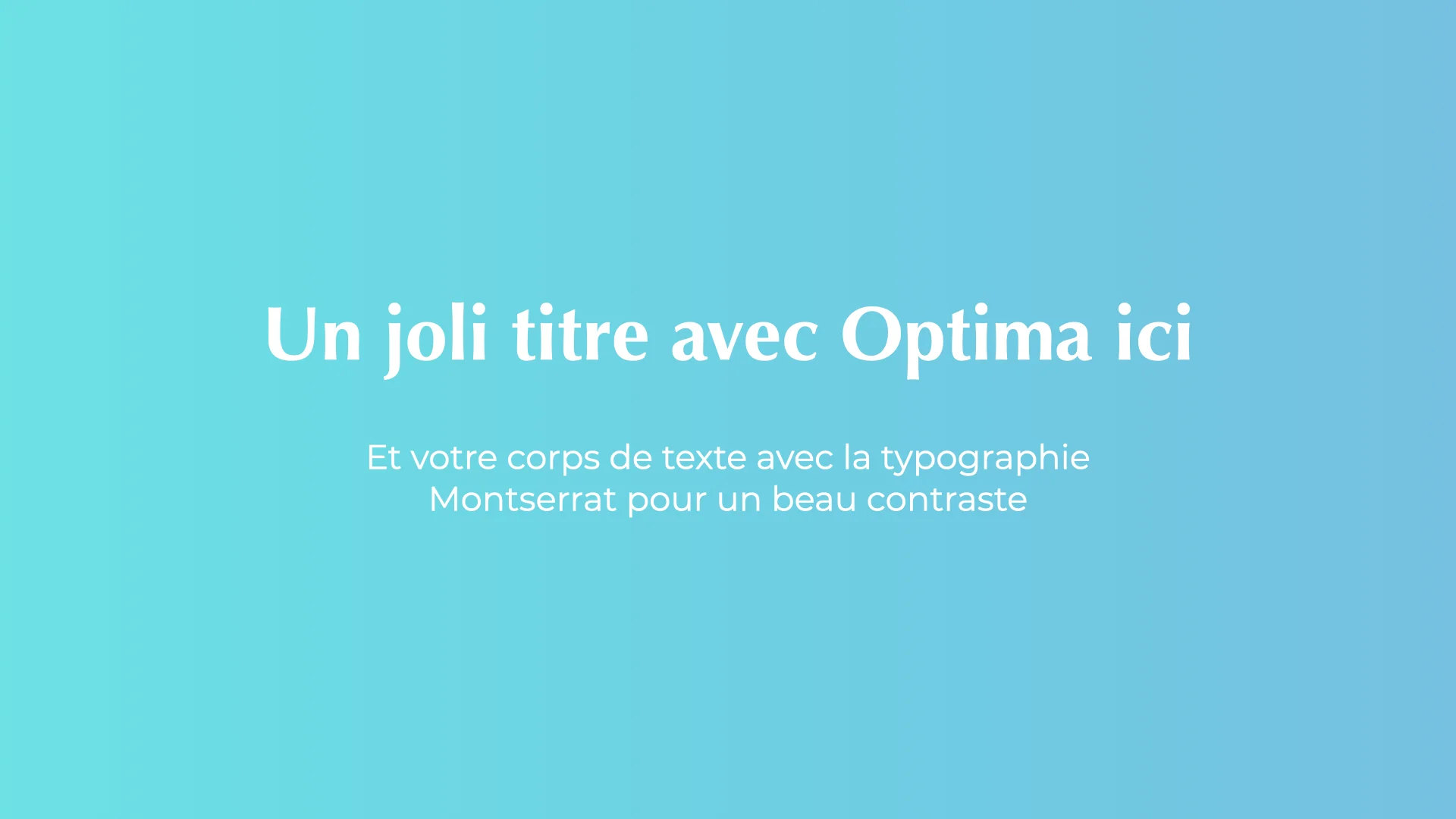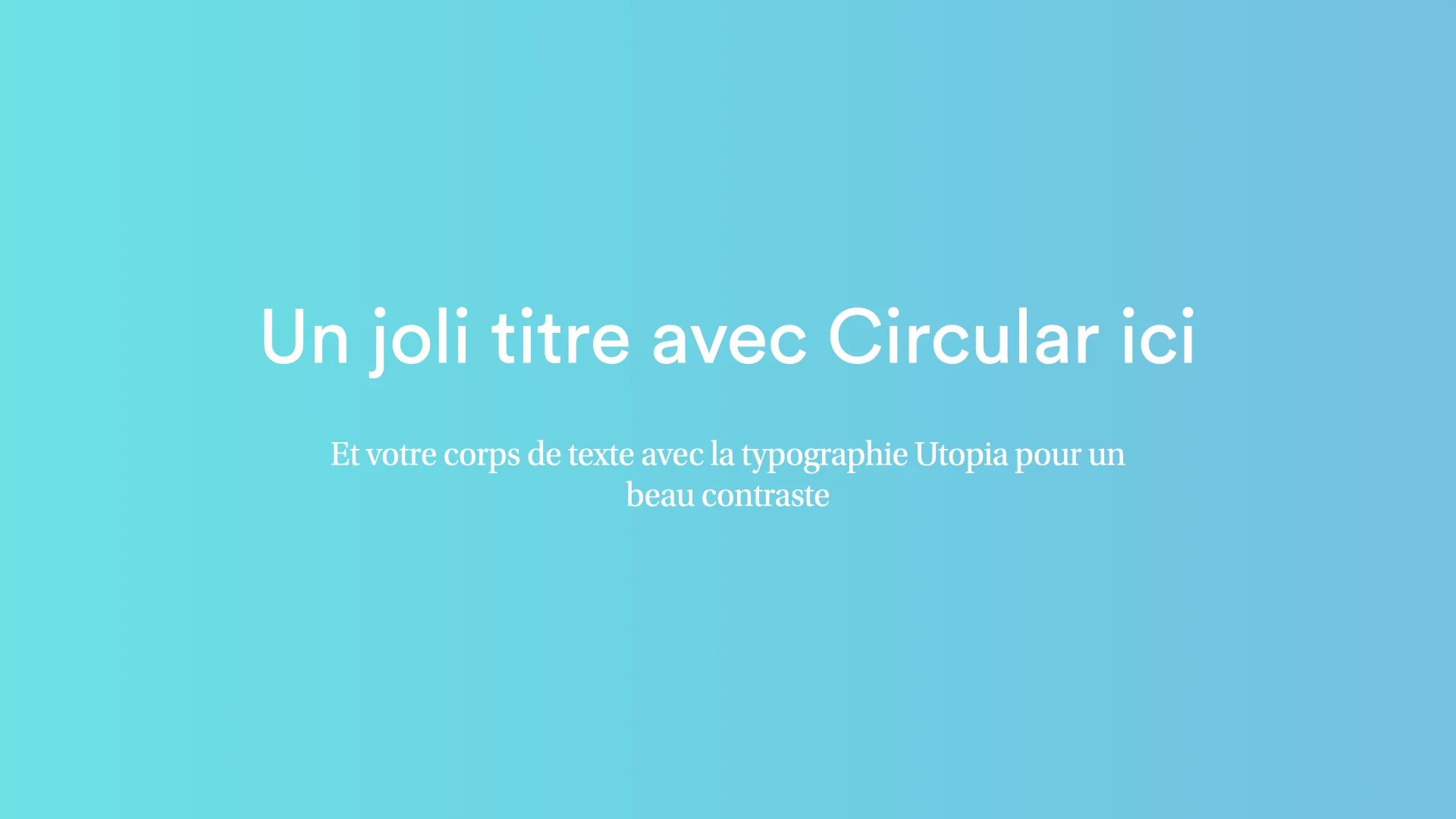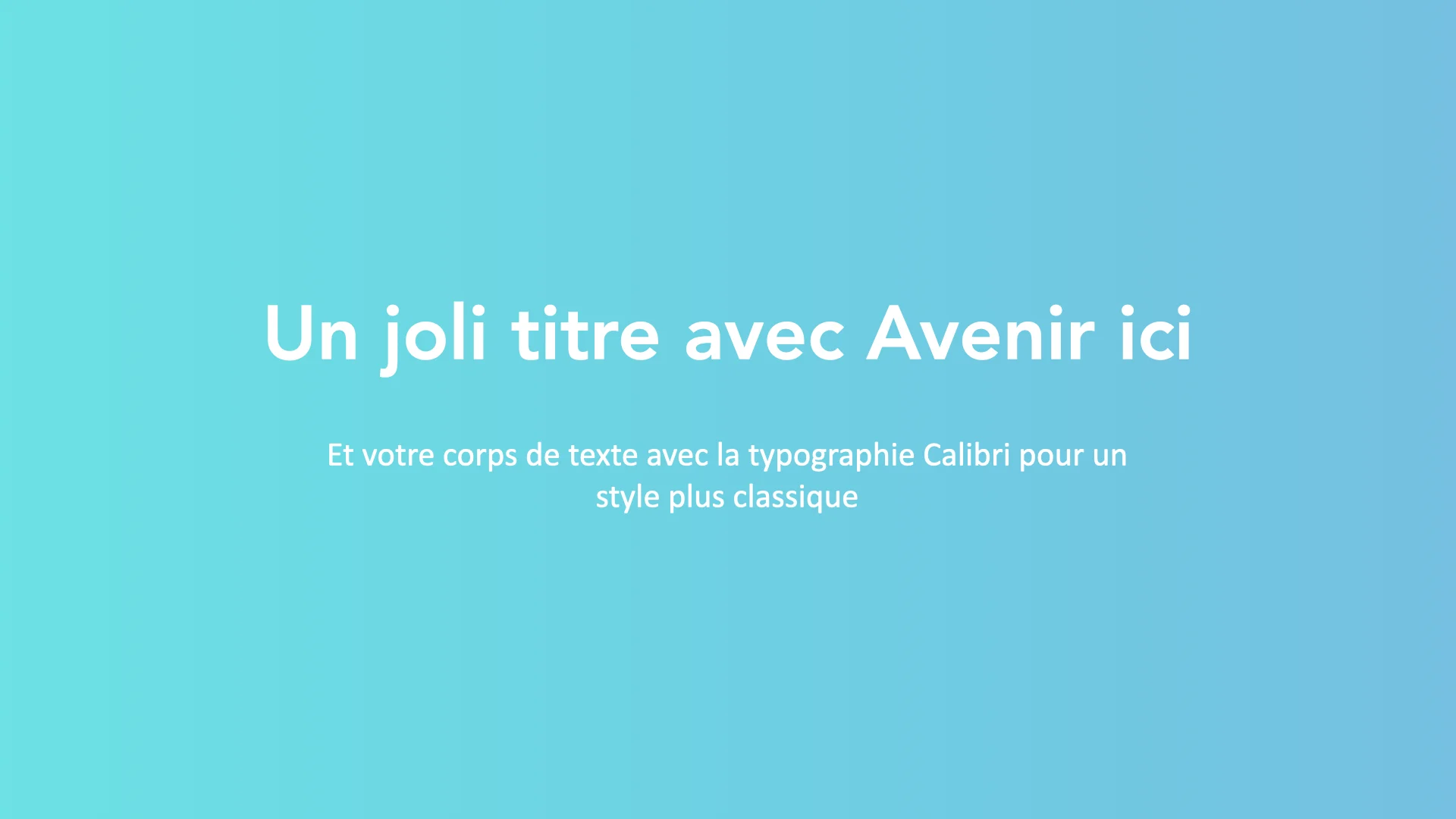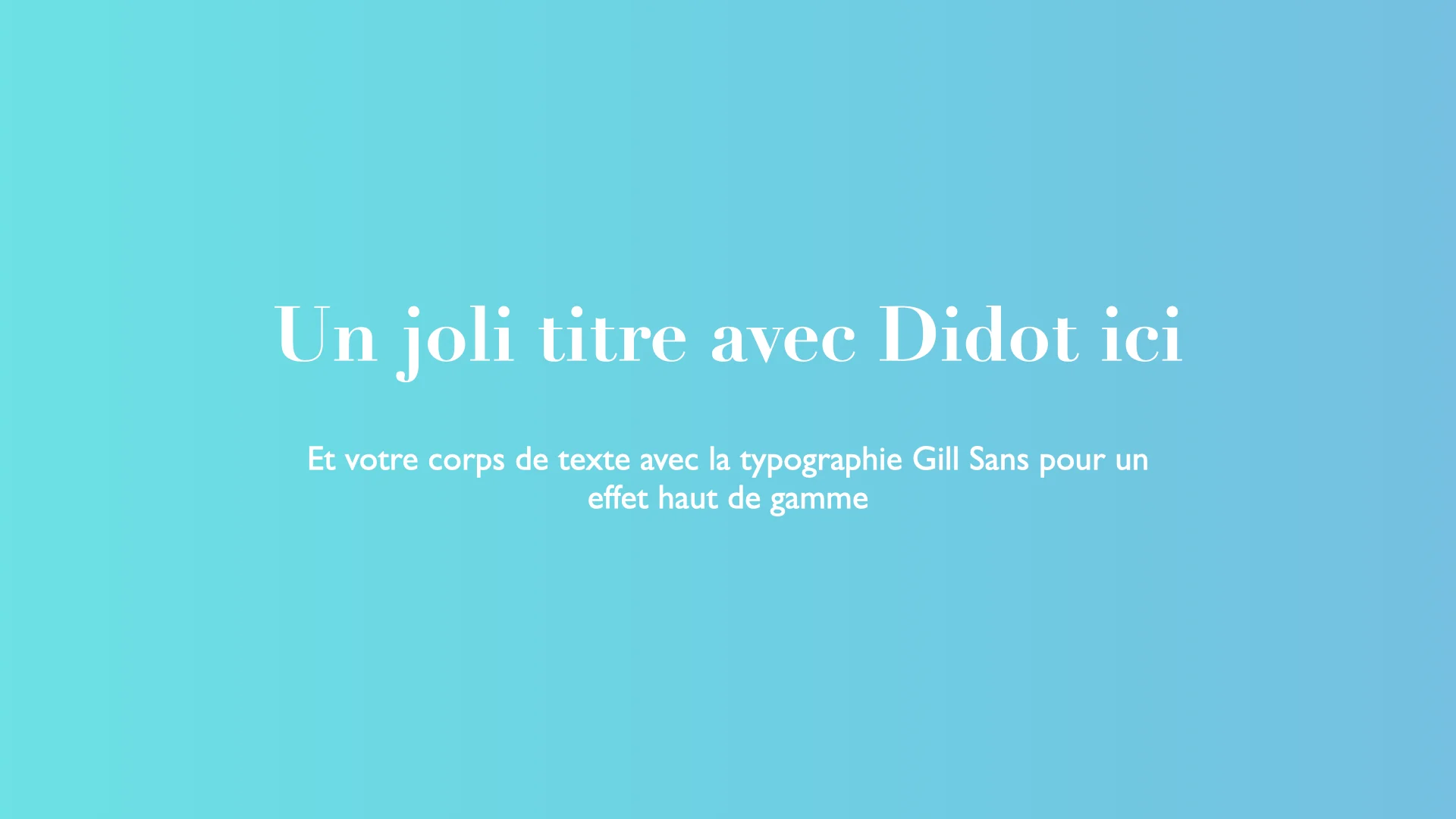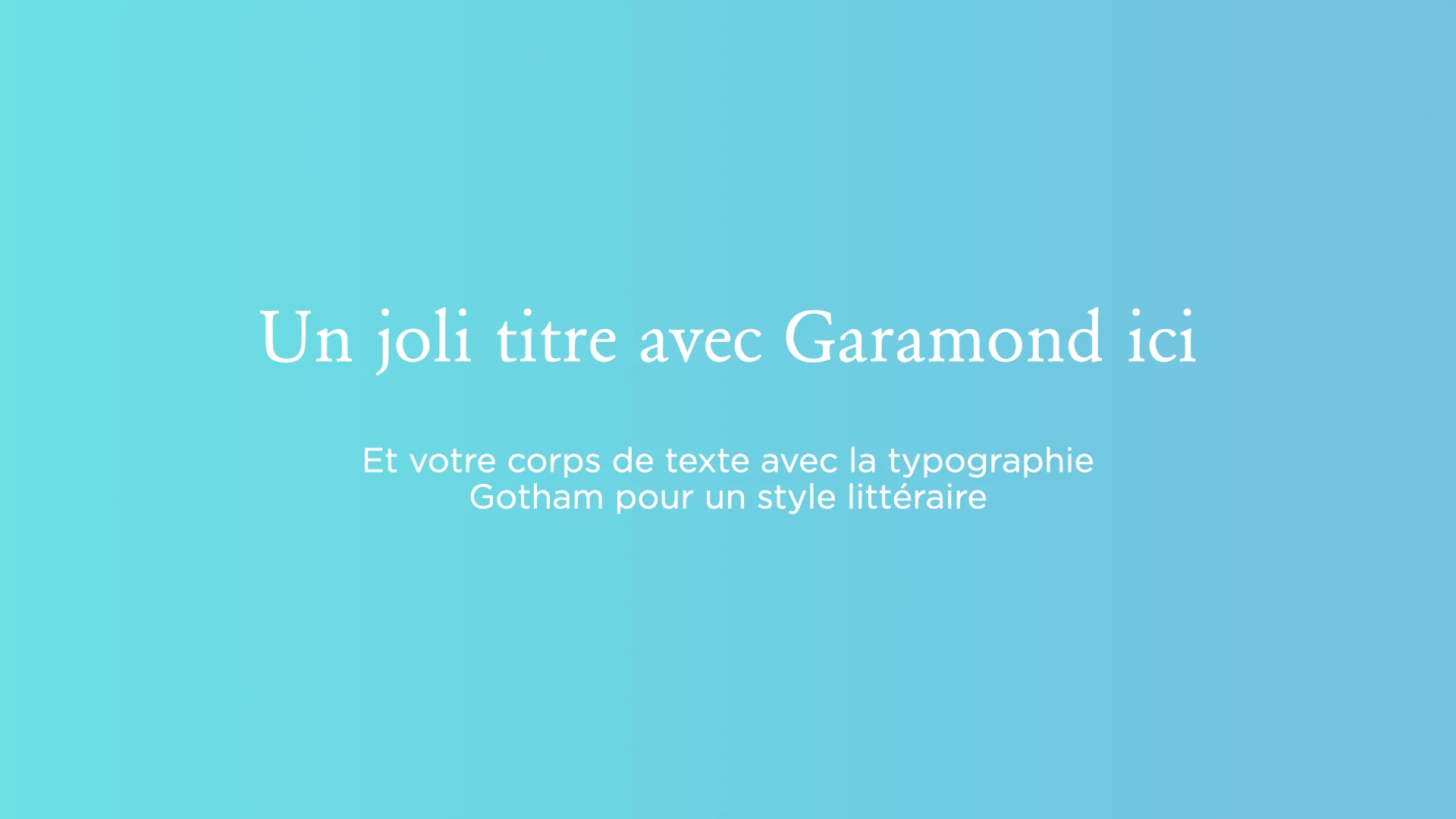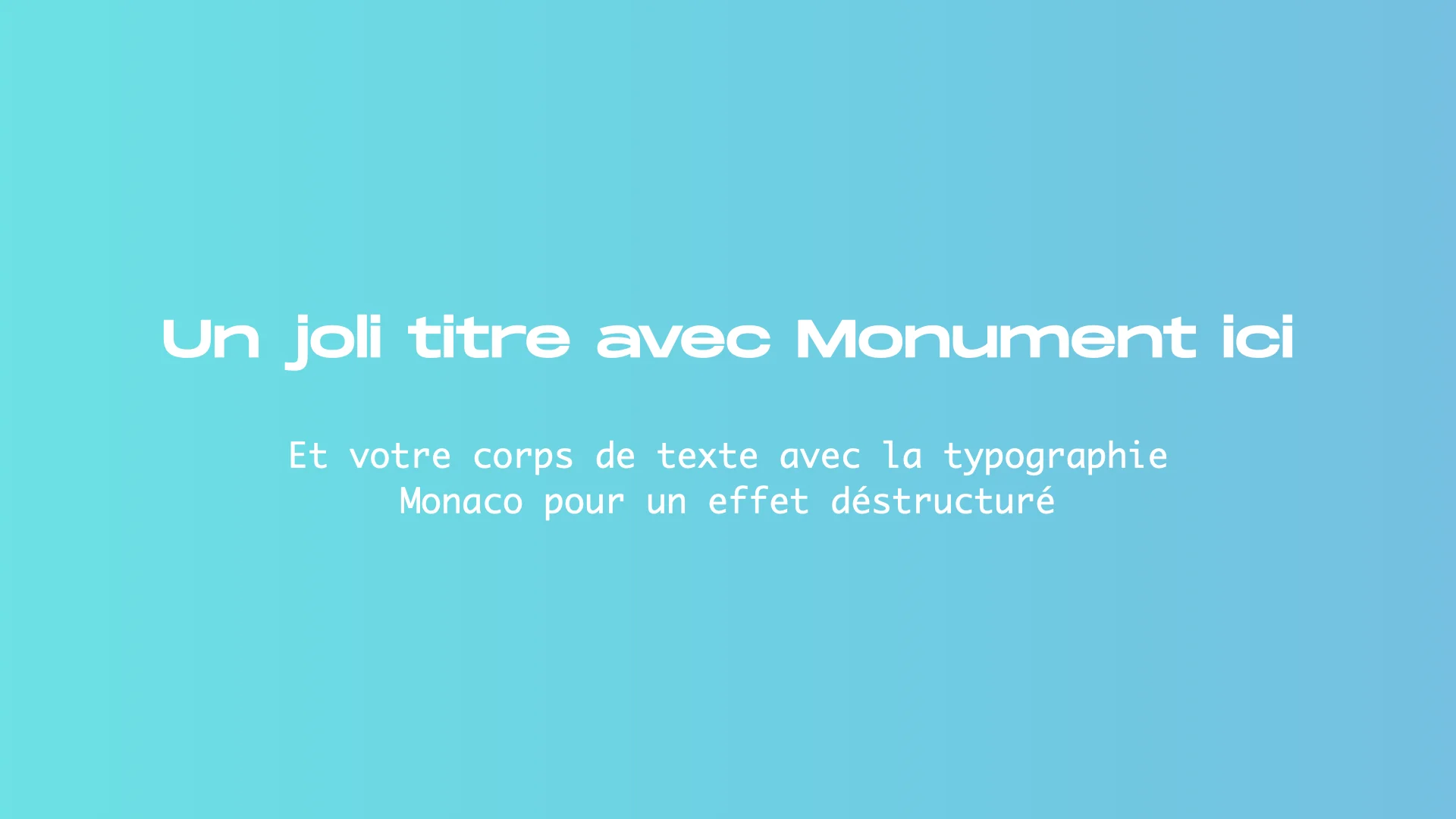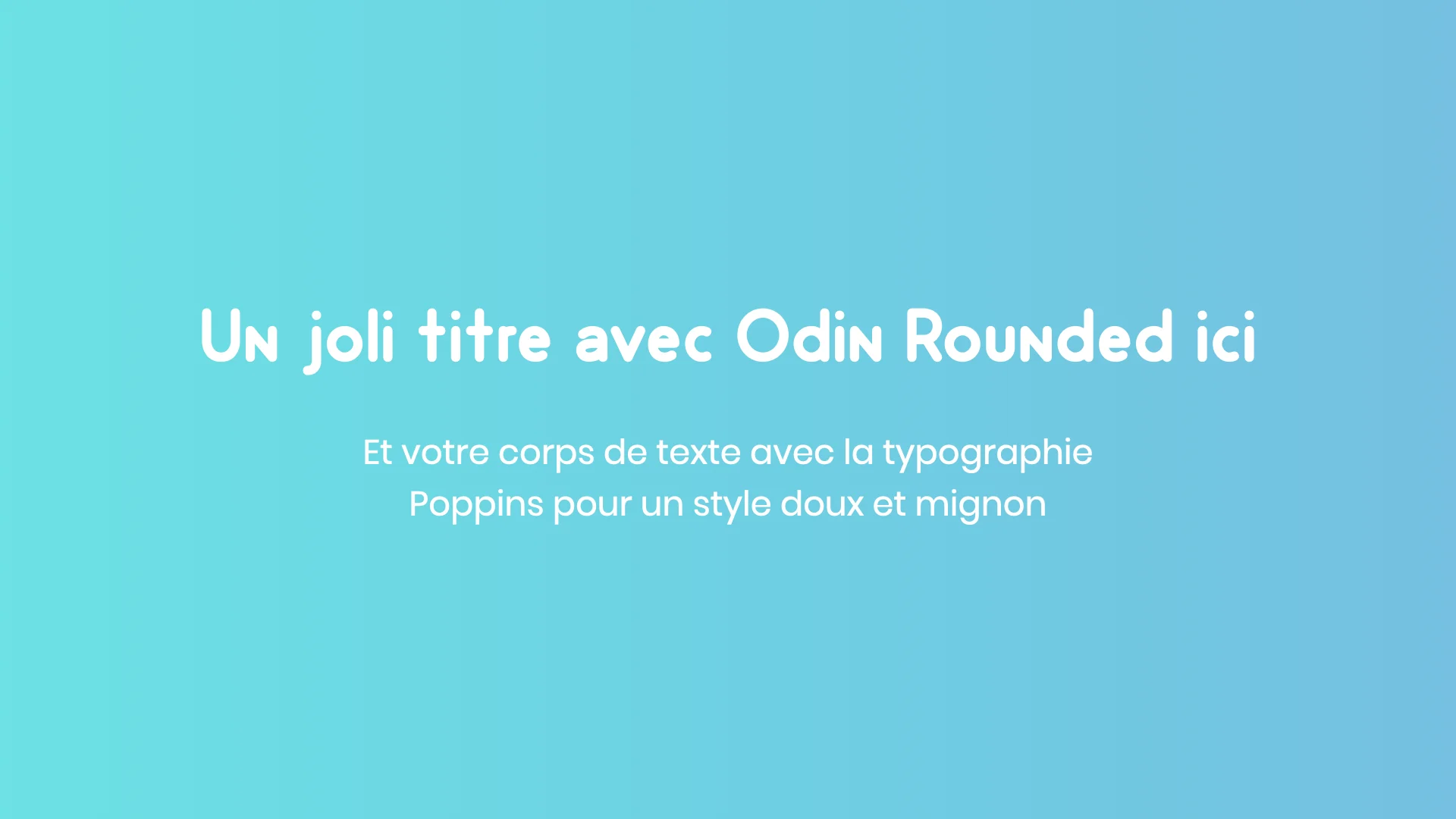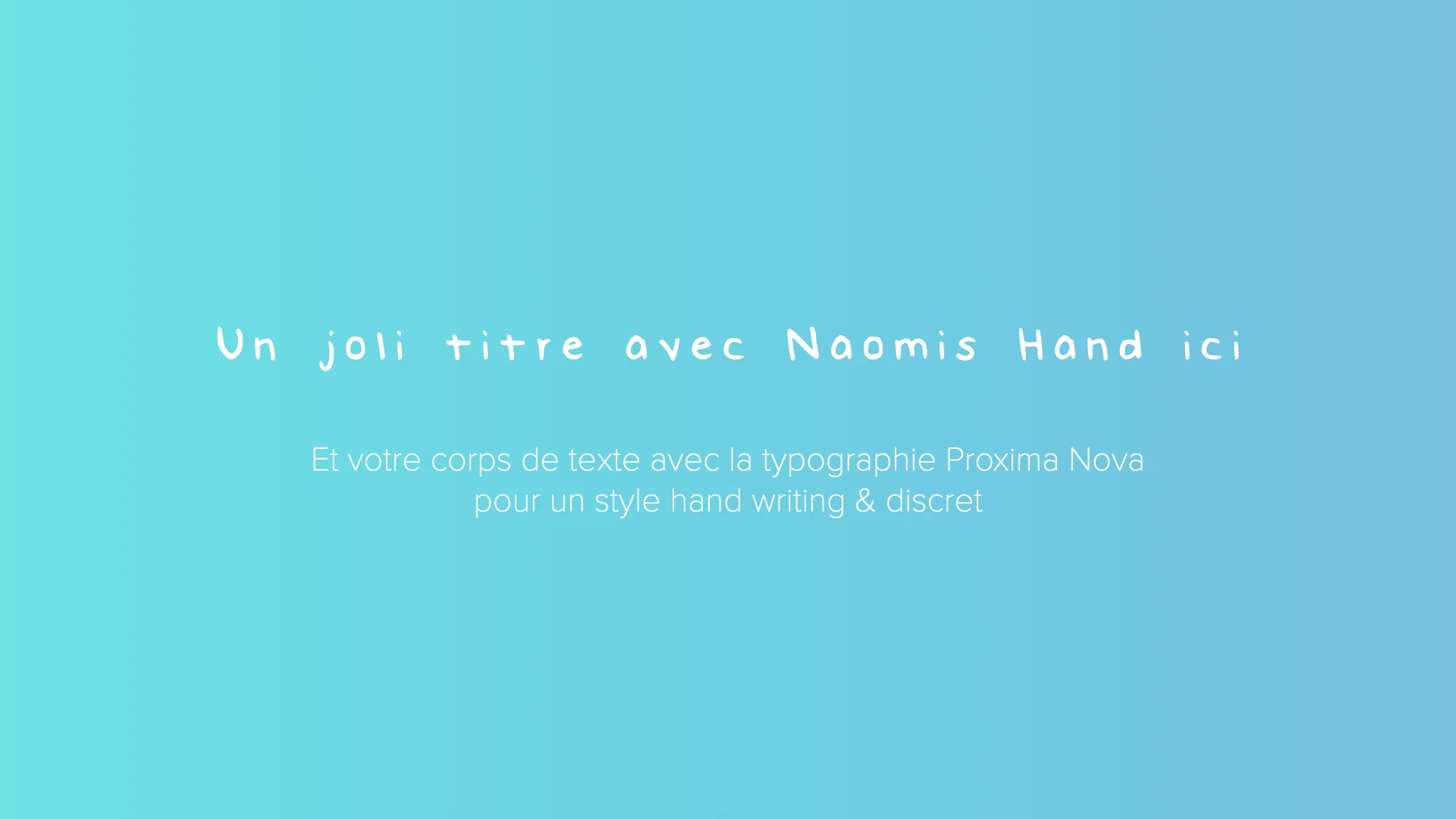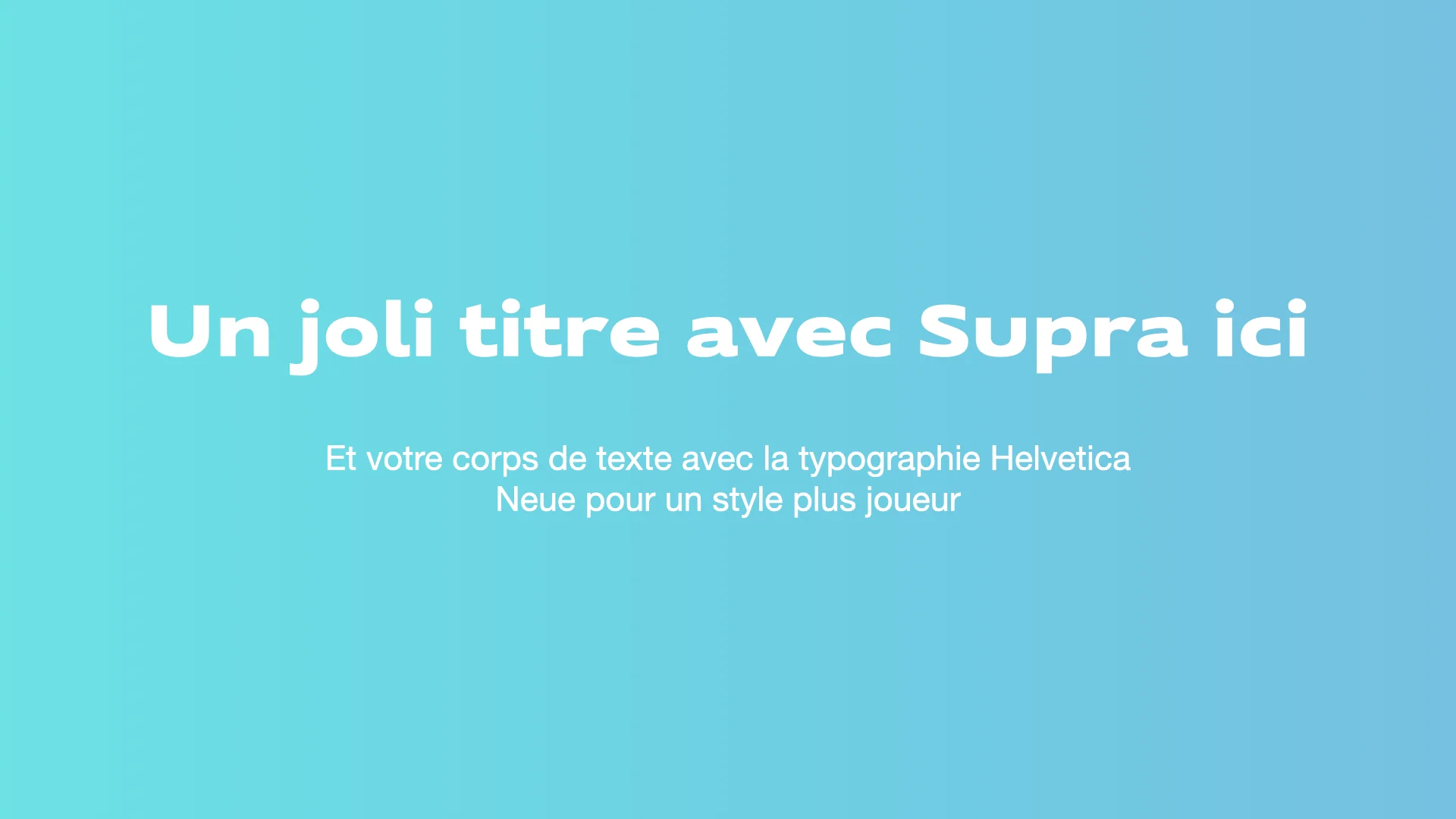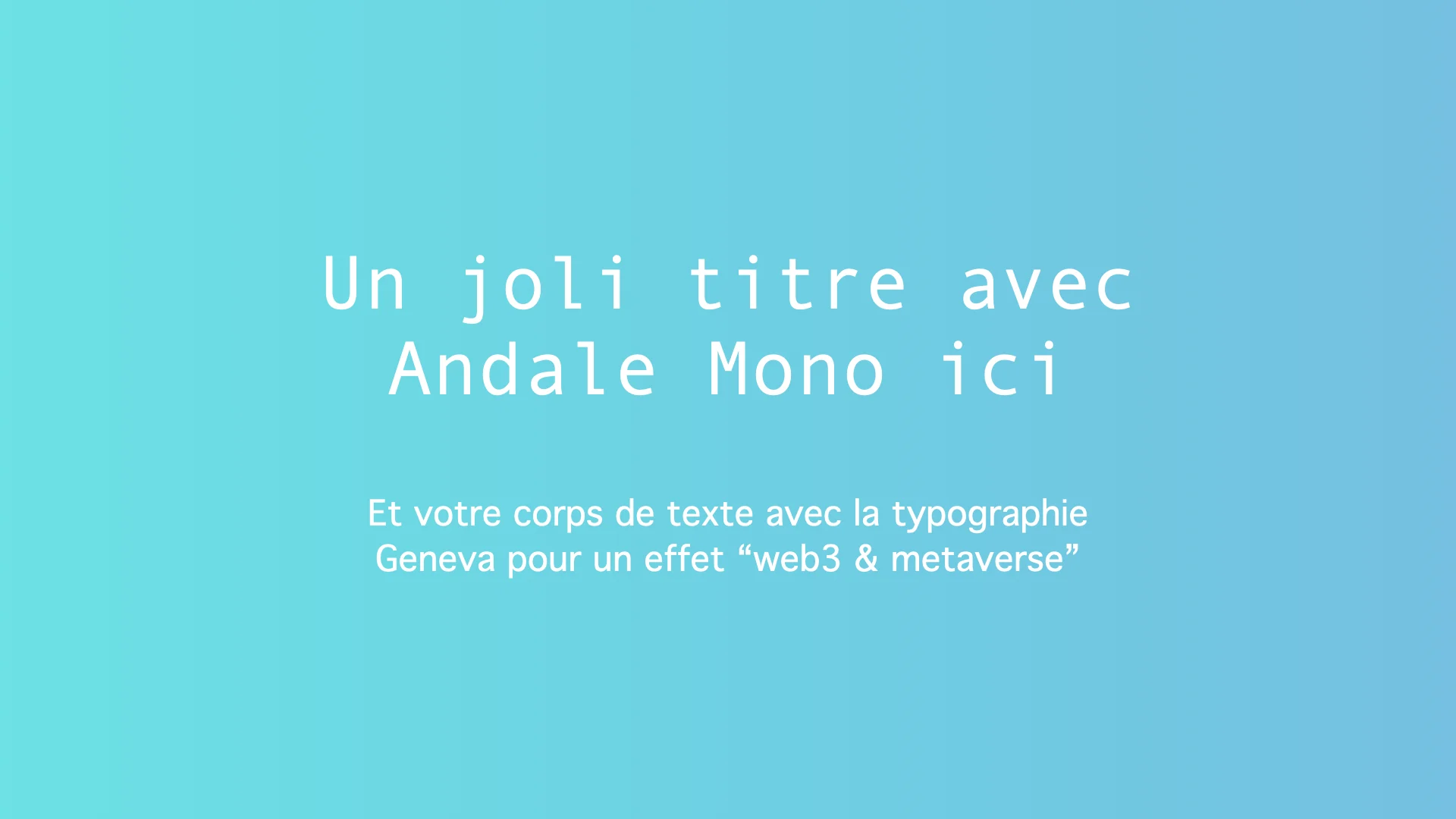
10 combinaisons de typographies pour vos projets 💑
Trouver des typographies complémentaires, ce n’est pas de tout repos. C’est pourquoi on vous propose aujourd’hui quelques idées faites maison histoire de vous aider dans vos recherches… et booster votre inspiration !
Quand on se lance dans un projet, que ce soit un nouveau business, une direction artistique pour une marque ou une présentation Keynote, il est essentiel de bien choisir ses typographies. En effet, vous le savez, elles symbolisent plus qu’une simple écriture. Elles permettent de véhiculer une idée, faire entrer un lecteur dans un univers, une atmosphère.
Cela parait plutôt logique, mais il est essentiel de rappeler qu’une bonne association de polices fait partie intégrante d’une charte graphique, que ce soit pour un simple visuel ou pour une plateforme de marque. Pourtant, c’est parfois difficile de trouver de bonnes combinaisons en fonction du message qu’on veut véhiculer. Généralement, on utilise une typographie plus originale pour les titres et une plus classique pour le corps de texte. Cependant il n’y a pas de règles dans tout ce qui touche au domaine créatif. Disons que c’est surtout le bon goût qui primera.
Alors pour vous aider dans vos recherches et vous proposer quelques idées, voici ci-dessous 10 combinaisons pour vos projets :